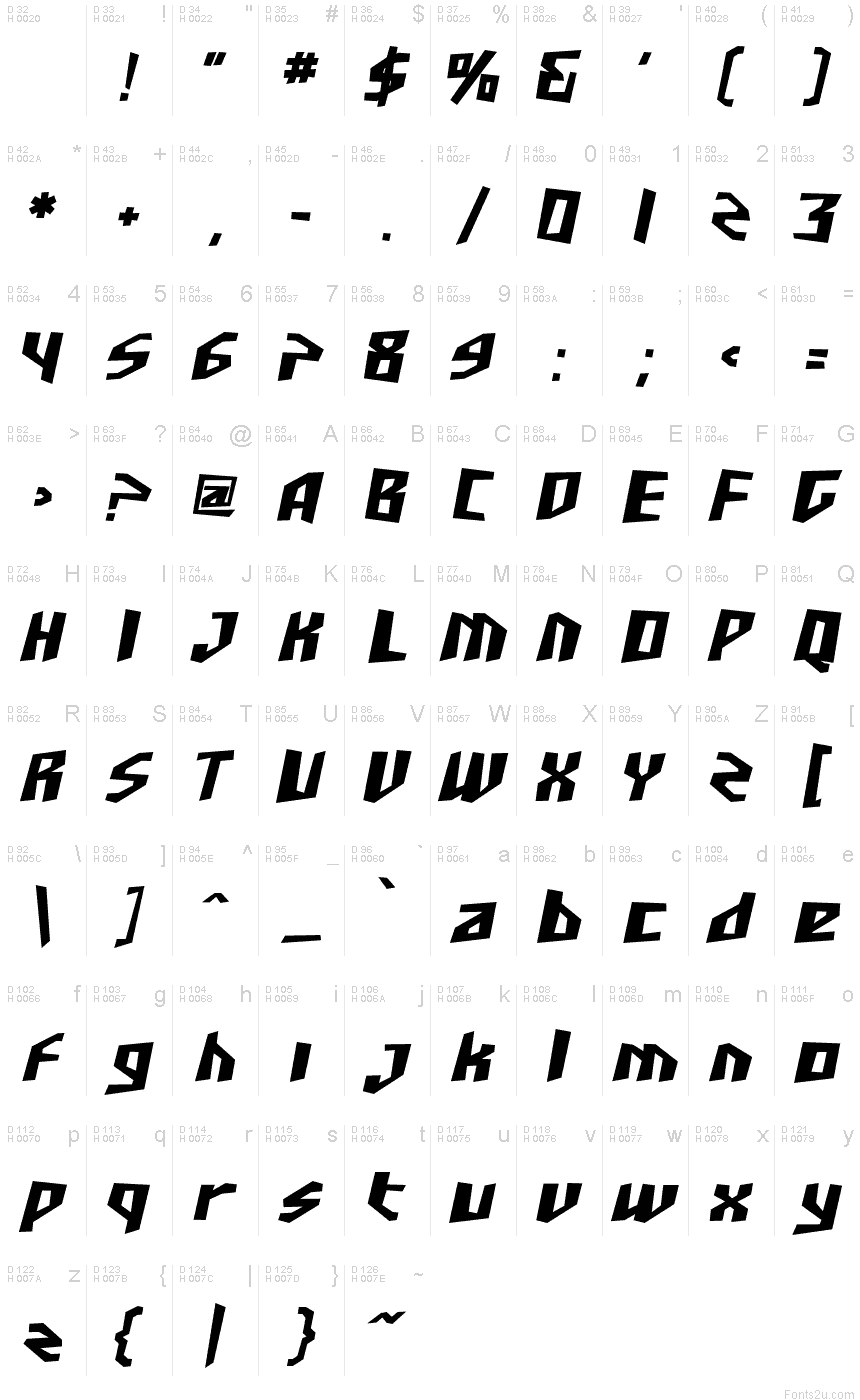
Podgląd czcionki SF Junk Culture Bold Oblique
SF Junk Culture Bold Oblique od ShyFonts Type Foundry to darmowy, komiksowy font typu display o ostrym, przypominającym wycinankę z papieru nachyleniu i celowo niepokornym charakterze. Litery wyglądają, jakby zostały wyciosane z grubych bloków, z poszarpanymi kątami, nierównymi szczytami i energią ulicznego fanzinu, która bardziej przywodzi na myśl punkowy kolaż niż grzeczny rysunek.
Dzięki temu świetnie sprawdza się w plakatach, grafikach na mixtape'y czy klubowe ulotki, brandingu skate lub streetwear, tytułach komiksów i mocnych nagłówkach, które wymagają wizualnego „kopa”. Jako darmowy font najlepiej sprawdza się w krótkich formach – strome nachylenie oraz masywne, posiekane kształty nadają charakteru nawet pojedynczym słowom.